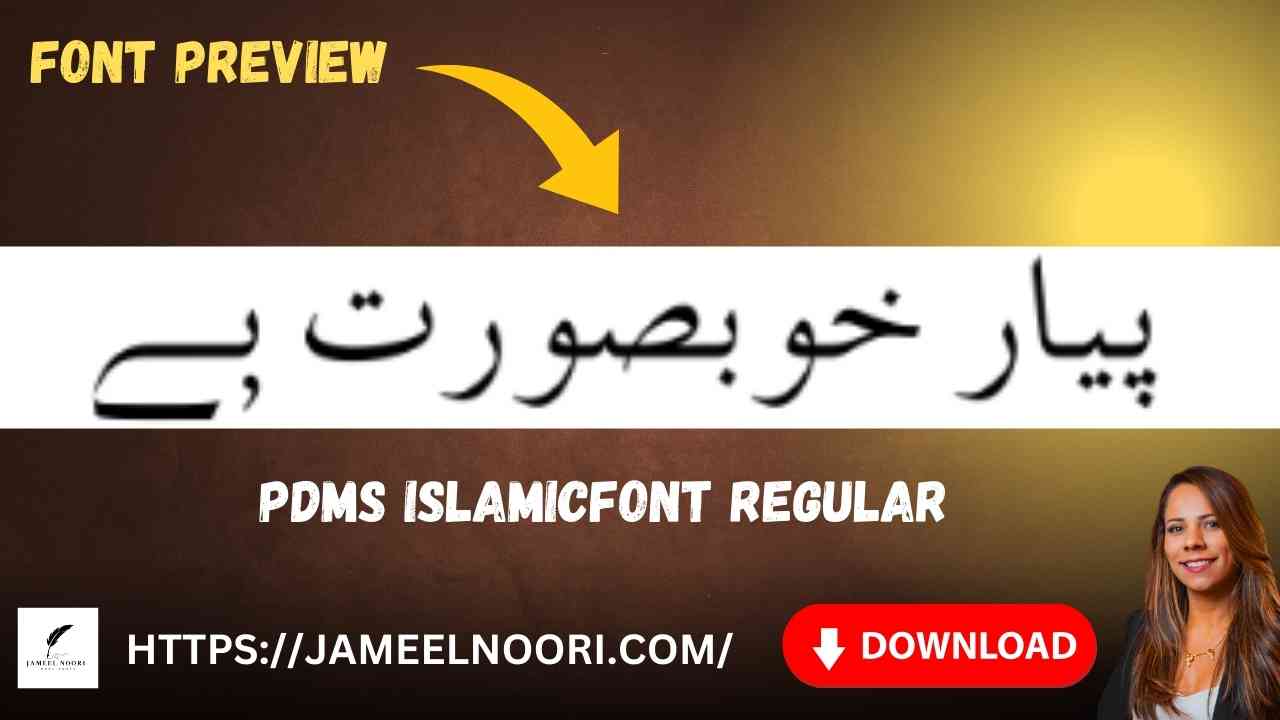
Agar aap Urdu likhne ya designing ke shaukeen hain to aap ke liye Download Urdu font PDMS IslamicFont Regular ek best option hai. Ye font ek Regular TrueType Font hai jo specially Urdu scripts ke liye design kiya gaya hai. Iska clean aur balanced design Urdu typing, assignments, aur publishing ke liye professional look deta hai.
Pakistan mein graphic designers aur students is font ko baray shauq se use karte hain kyunke iska style simple, easy-to-read aur attractive hai. Ye font InPage, MS Word, Photoshop aur CorelDraw jaise software ke sath smoothly compatible hai. Agar aap apne Urdu fonts collection mein ek elegant aur reliable font add karna chahte hain to PDMS IslamicFont Regular aapke liye perfect choice hai.
Features of Urdu font PDMS IslamicFont Regular
Download Urdu font PDMS IslamicFont Regular ke kuch khas features yeh hain:
- Usage: Document writing, Urdu designing aur Quranic scripts ke liye best choice.
Why Choose Download Urdu font PDMS IslamicFont Regular in Pakistan
Pakistan me designers aur students ke liye ye font aik affordable aur reliable option hai. Aap ise har type ke graphic designing software me use kar sakte hain jaise Photoshop, CorelDraw, aur InPage.
Iske kuch reasons jo isse popular banate hain:
- Simple aur clear writing style
- Easy readability for Urdu text
Benefits of Using Download Urdu font PDMS IslamicFont Regular
Download Urdu font PDMS IslamicFont Regular ke benefits ye hain:
- Professional look for documents
- Suitable for both personal aur official kaam
Agar aap ek simple, reliable aur easy-to-use Urdu font dhoondh rahe hain to Download Urdu font PDMS IslamicFont Regular aapke liye perfect hai. Pakistan ke students, teachers aur designers is font ko baray arsay se use kar rahe hain aur iska feedback bhi positive hai. Abhi download karke apne Urdu projects ko ek naya look dein.